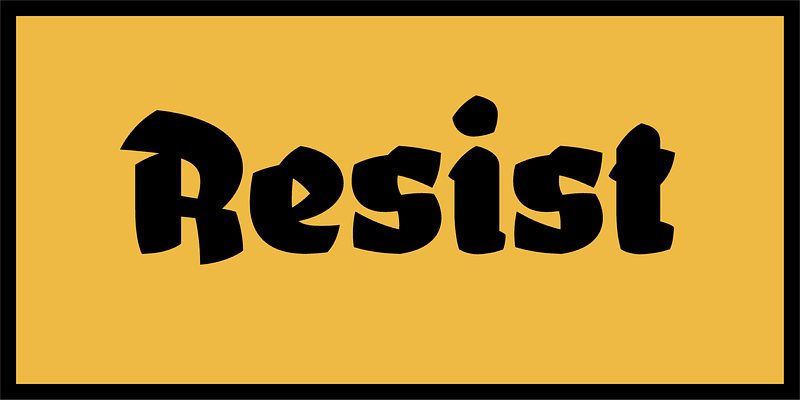
„Sie ist täuschend einfach in ihrer Erscheinung. Aber als jemand, der versucht hat, die Art von Zeichen zu entwerfen, die sich in einem von Lucian Bernhards Plakatstil-Designs zu Hause fühlen würden, respektiere ich Schneider dafür, dass er eine Schrift geschaffen hat, die sich so authentisch anfühlt, weil sie ihre Wurzeln respektiert, ohne jedoch mit Pastiche gespickt zu sein. Die scharfen Kanten und die effizient reduzierten Formen der Paroli haben ihren Ursprung in handgezeichneten Zeichen, die an Minimalismus grenzen, kurz bevor ihr Charakter verschwindet. Die Ausbuchtungen und partiellen Verbindungen der Pinselstriche sind gut platziert und tragen dazu bei, die wunderbaren formalen Exzentrizitäten der mit solchem Gewicht ausgeführten Schwarzschrift zu bewältigen. Aber dieses ‘bürstige Temperament’ verleiht Paroli einen freundlichen Schwung und einen lebendigen Rhythmus, die der oft kriegerischen Natur der Schwarzschriftformen entgegenwirken. Paroli ist aufgrund ihrer visuellen Herkunft natürlich begrenzt, aber ich denke, es lohnt sich, sie für jede große, fette Schriftsatzsituation im Hinterkopf zu behalten, in der nur ein paar Wörter die ganze schwere Arbeit machen und ein einzigartiger Charakter gefragt ist.“ von Chris Rugen